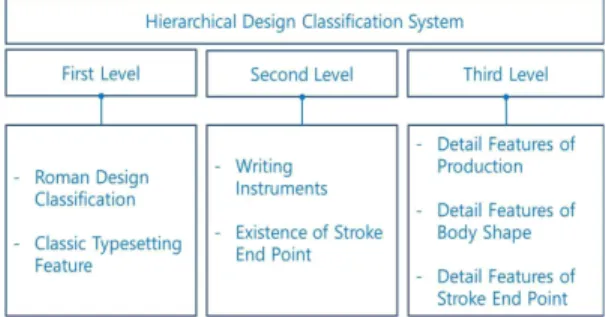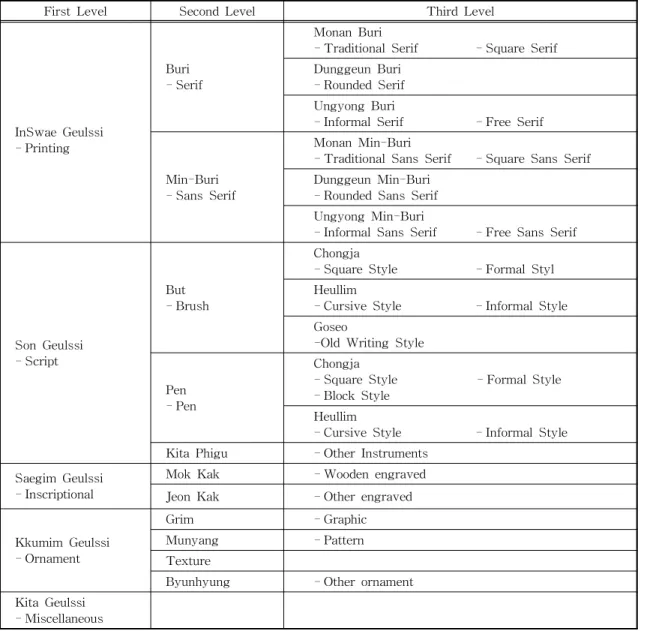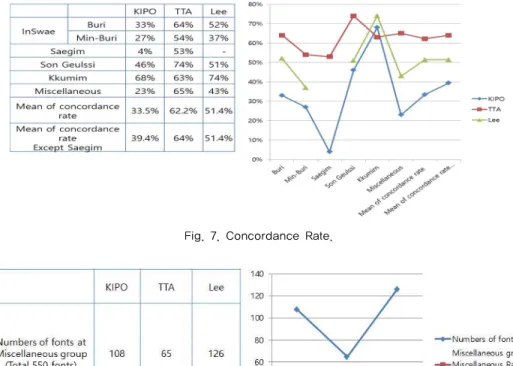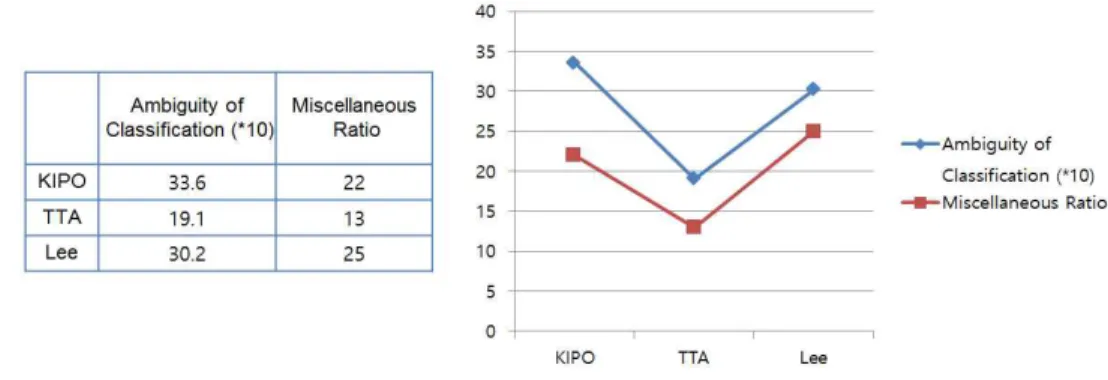
한글 글꼴 등록 시스템을 위한 글꼴 모양 분류체계 표준화 연구
Standardization Study of Font Shape Classification for Hangul Font Registration System
ABSTRACT
Recently, there are many communication softwares based on text on various smart devices. Unlike traditional print publishing, mobile publishing and SNS tools tends to utilize more decorative or more emotional fonts so that users can pass some feelings from contents. So font providers have released new fonts which deal with the requirements of the market. Nevertheless being released lots of new fonts, general users have not used them because they searched only by font name or font provider’s name.
It means that there is no way for users to know and find new things. In this study, we suggest font shape classification rules for font registration system based on font design features. We proved the validity of classification standard study through some experiments with 50 commercial fonts. Also the result of this study was provided for Korea Telecommunication Technology Association and adopted by the Korea industrial standard.
1. 서 론
모바일 스마트 디바이스 환경을 맞이하여, 종이출 판 시대의 고전적 명조 및 고딕 글꼴로 한정되어 사 용하던 시장과 다르게, 게임과 웹툰, 전자책, 동영상 프로그램 자막, 소셜 미디어 등의 모바일 환경을 위 한 세련되고 재미있는 글꼴들이 대량 출시되면서 적 절한 글꼴 및 글꼴 동작을 통해 감성을 풍부하게 하 고 의미 있는 의사전달[1,2,3]을 시도하고 있다.
현재의 한글 글꼴 등록 시스템이나 검색 시스템에 서는 한글 글꼴 시스템의 특수성을 반영하지 못하고
단순하게 글꼴 명이나 글꼴 제작사를 알아야만 검색 하여 사용이 가능한 상황이어서 육 천종이상의 상용 한글 글꼴[4]에 대한 특징을 반영한 사용이 불가능하 였다.
또한 글꼴제작사가 자신의 글꼴만을 판매하던 패 키지상품 형태의 영업에서 벗어나 Cloud 환경에서 라이선스에 기반 한 글꼴 서비스 형태로 영업 방식이 변경되면서 한 글꼴 사이트에서 여러 글꼴제작사의 글꼴을 통합적으로 등록하고 관리해야하는 공급환 경으로 변경되었다. 그러나 여전히 현재의 문제를 가 지고 있음으로 글꼴 이름과 제작사명에만 의존하여
Fig. 1. Google Font Service with 5 categories.
(a) Sandoll Cloud (b) Yoon Font Cloud Service Fig. 2 Hangul Font Service Sites.
몇 천종의 글꼴을 등록 관리하고 검색하는데 관리 측면에서 뿐 아니라 사용자 측면에서 비용 및 시간적 비효율성이 발생하고 있다. 따라서 체계적인 한글서 비스를 위하여, 글꼴의 시각적 디자인 기반의 등록시 스템이 필요하며 특히 사용자가 직관적인 검색을 통 해 서비스를 받을 수 있도록 디자인 기반의 글꼴 분 류체계가 요청된다.
이에 한글 글꼴 등록 시스템을 위한 디자인 분류 체계용 표준연구가 필요한 시점이다. 이번 연구의 결 과는 한국정보통신기술협회의 전자출판분과 PG608 에 한글 글꼴 디자인 분류 표준[5]으로 제안하여 심 의와 수정을 거쳐 산업계 표준안으로 2016년 6월24 일자로 채택되었으며 한글등록 사이트인 한글마을 [6]을 통해 사용성을 검증하였다.
2. 기존 연구 및 글꼴 서비스 사례 조사
2.1 국내외 글꼴 검색 서비스에서 분류체계 대표적인 영문글꼴 서비스 사이트에서 사용하는 분류체계를 조사하여 한글 글꼴 서비스에서의 분류 체계를 구체화하여 본다. 구글 글꼴 사이트인 구글폰 트[7]는 Fig. 1에서 보듯이 Serif, Sans Serif, Display, Handwriting, Monospace까지 5개의 디자인 분류기
준을 사용하였다.
구글 글꼴 서비스는 영어권용 글꼴만을 위한 것으 로 일본어, 중국어, 한글처럼 영문과 한자 등의 여러 언어권 문자가 통합된 글꼴은 서비스 하지 않음으로, 로마문자 디자인 분류체계에서 확연한 구분 특징을 가지는 5개의 분류 기준을 사용하고 있다.
일본어 서비스를 시작한 Adobe TypeKit 서비스 [8]는 영문 라틴의 분류체계로서 기존 사이트와 유사 한 Sans Serif, Serif, Mono, Hand, Decorative 5개의 분류기준과 Slab Serif, Script, Blackletter 3개의 새 로운 분류기준을 사용한다. 일본어 서비스에서는 Mincho, Gothic, Maru Gothic, Brush, Stylized, UD, Newspaper 등의 6개 디자인 분류기준을 채택하여 언어권별로 다른 분류기준을 사용하고 있는 것을 알 수 있으며 Mincho-Serif, Gothic-Sans Serif, Script- Bush 3 가지 분류기준의 관계를 제시하였다.
Fig. 2에서 볼 수 있듯이 대표 글꼴 사 윤디자인[9]
사이트의 폰트 보기 메뉴에서는 수백 종의 글꼴을 이름으로만 구분한다. 산돌[10] 사이트에서는 고딕, 디자인, 명조, 베이직, 손글씨, 옛글씨, 팬시 등의 7개 디자인 분류 안을 사용하며 디자인과 팬시의 개념이 겹쳐지고 베이직은 무엇을 기준으로 정의하는지 사 용 혼란을 주고 있다.
Fig. 3 Typeface design grouping with Japanese type- faces.
글꼴을 기획하고 제작하는 글꼴 사에서도 분류기 준이 일관성이 없고 상이하여 여러 글꼴사의 글꼴을 사용하는 사용자에게 혼란을 주고 있다. 결국 각 서 체사의 글꼴 소개 자료를 확인하거나 글꼴을 설치한 후 소프트웨어의 글꼴 리스트에서 직접 하나씩 확인 하며 사용해야 함으로 검색의 불편함과 비효율성이 개선되지 않고 있다.
2.2 다른 문화권 글꼴의 디자인 기반 분류체계 영어권에서 글꼴 분류체계를 처음으로 제시한 것 은 프랑스의 타이포그래피 역사가 막시밀리엉 복스 (Maximilien Vox)이며, 국제 타이포그래피 연맹 (ATypI: Association Typographique International) 에 의해 표준 분류법으로 채택되면서 VOX-ATypI 분류법[11,12]으로 정의되어 유럽의 여러 국가에서 표준이 되는 분류체계로 인정을 받아왔다.
데스크 탑 퍼블리싱 환경에서 조판을 진행하기 위 한 글꼴의 분류법이 더욱 요구되었으며, 분류의 정보 를 글꼴 포맷 내부에 저장하여 필요한 조판시점에 바로 활용하고자하는 시도가 IBM[12]을 중심으로 이루어졌다.
그러나 두 분류법 모두는 영어권의 라틴문자만을 처리함으로 모든 언어권의 글꼴에 적용하기에는 부 족함이 있었고, 따라서 다른 문화권의 언어에도 적용 할 수 있는 ISO/IEC 9541-1:2011 Information tech- nology — Font information interchange [13] 표준안 이 발표되었다.
이 표준 문서는 글꼴 정보 교환 표준 문서의 부속 서로, 여기에 포함된 언어는 영어권, 아랍어권, 한자 권, 일본어권 등의 4개 문화권을 포함하고 있으며, 크게 7개의 그룹 Uncials, Inscriptionals, Blacklet- ters, Serifs, Sans Serifs, Script, Ornamentals 으로 분류하고 이를 다시 세분화하여 143개 소분류로 나 누는 3단계 분류법을 사용하고 있다.
일본어는 Fig. 3에서 볼 수 있듯이 Inscriptionals, Serifs, Sans Serifs, Script, Ornamentals 등의 5개 그룹에 주로 위치하고 있다. 그러나 자세히 살펴보면 전체 143개 소 분류그룹 중에 7%에 해당되는 10개 그룹에만 글꼴 분류되어 있어 외국어 영역의 강화가 필요하다. 또한 아쉽게도 표준안에서 한글 글꼴에 대 한 언급이 없으며 글꼴 정보 교환을 위한 표준 문서 의 정규 내용 아닌 부속서 형태로 정리되어 있다.